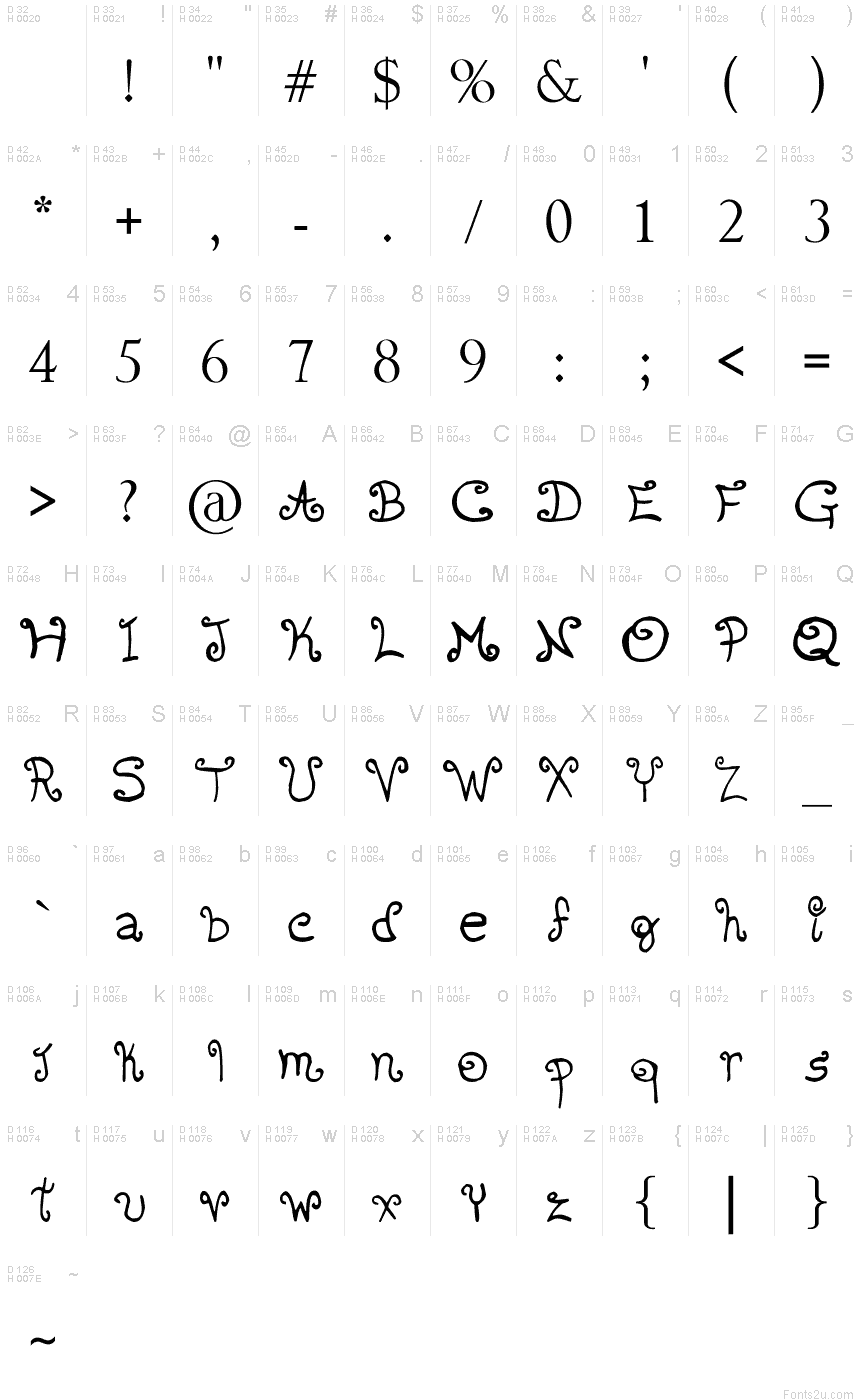
Romantic font 2 to darmowy, dekoracyjny krój pisma pełen loków, utrzymany w romantycznym, baśniowym klimacie. Litery opierają się na szerokich, miękkich pociągnięciach i przerysowanych pętlach, które wielokrotnie zawijają się do środka. Nadaje to krojowi rękodzielniczego, niemal średniowiecznego charakteru, co odróżnia go od nowoczesnych, grzecznych pism odręcznych.
Pasuje idealnie do zaproszeń, opakowań butikowych, identyfikacji wizualnej kawiarni, okładek książek i nagłówków na plakatach – wszędzie tam, gdzie darmowy font ma wnieść dekoracyjny nastrój bez konieczności dodawania kolejnych ozdobników. Używaj go do krótkich tytułów, imion czy inicjałów w formie monogramów: te hojne zawijasy robią całą robotę za Ciebie, a zaokrąglone kształty sprawiają, że całość jest ciepła w odbiorze i wcale nie przytłacza.